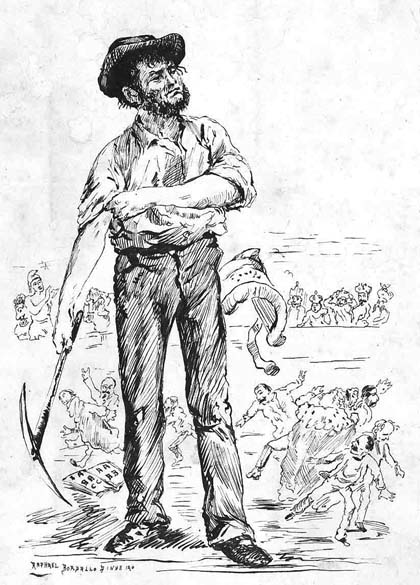
Raphael Bordallo Pinheiro (1846 1905)Ilustrador de dezenas de livros e publicações, precursor do cartaz artístico em Portugal, decorador, caricaturista político e social, jornalista, ceramista e docente. Artista da Litografia.Um nome que está intimamente ligado à caricatura portuguesa, à qual deu um grande impulso, imprimindo-lhe um estilo próprio levando a uma visibilidade nunca antes atingida. Autor da figura popular Zé Povinho que se veio a tornar num símbolo do povo português. Nasceu em 1846 em Lisboa. Cedo ganha o gosto pelas artes. Em 1860 inscreve-se no conservatório e posteriormente matricula-se sucessivamente na Academia de Belas Artes (desenho de arquitectura civil, desenho antigo e modelo vivo), no Curso Superior de Letras e na Escola de Arte Dramática, para logo de seguida desistir. Começa por tentar ganhar a vida como artista plástico com composições realistas apresentando pela primeira vez trabalhos seus em 1868 na exposição promovida pela Sociedade Promotora de Belas-Artes, onde apresenta 8 aguarelas inspiradas em costumes e tipos populares. Em 1871 recebe um prémio na Exposição Internacional de Madrid. Paralelamente vai desenvolvendo a sua faceta de ilustrador e decorador. Em 1875 cria a figura do Zé Povinho, publicada n'A Lanterna Mágica. No BrasilEm 1875 parte para o Brasil onde colabora em alguns jornais e a enviar a sua colaboração para Lisboa, voltando a Portugal em 1879 e lança O António Maria. LitografiaComo litógrafo, Bordalo Pinheiro deixou um legado notável. Compôs desenhos para almanaques, anúncios e revistas estrangeiras como El Mundo Comico (1873-74), Ilustrated London News, Ilustracion Española y Americana (1873), L'Univers Illustré e El Bazar. Fez desenhos em álbuns de senhoras, foi o autor de capas e de centenas de ilustrações em livros, e em folhas soltas deixou portraits-charge de diversas personalidades. Começou a fazer caricatura por brincadeira como aconteceu nas paredes dos claustros do edifício onde dava aulas o Professor Jaime Moniz, onde apareceram, desenhados a ponta de charuto, as caricaturas dos mestres. Mas é a partir do êxito alcançado pel'O Dente da Baronesa (1870), folha de propaganda a uma comédia em 3 actos de Teixeira de Vasconcelos, que Bordalo entra definitivamente para a cena do humorismo gráfico. Dotado de um grande sentido de humor, mas também de uma crítica social bastante apurada e sempre em cima do acontecimento, caricaturou todas as personalidades de relevo da política, da Igreja e da cultura da sociedade portuguesa. Apesar da crítica demolidora de muitos dos seus desenhos, as suas características pessoais e artísticas cedo conquistaram a admiração e o respeito público que tiveram expressão notória num grande jantar em sua homenagem realizado na sala do Teatro Nacional D. Maria II, em 6 de Junho de 1903 que, de forma inédita, congregou à mesma mesa praticamente todas as figuras que o artista tinha caricaturado. Na sua figura mais popular, o Zé Povinho, conseguiu projectar a imagem do povo português de uma forma simples mas simultaneamente fabulosa, atribuindo um rosto ao país. O Zé Povinho continua ainda hoje a ser retratado e utilizado por diversos caricaturadores para revelar de uma forma humorística os podres da sociedade. Cerâmica nas Caldas da RainhaExperimenta em 1885 trabalhar o barro e começa o fabrico da louça artística das Fábrica de Faianças das Caldas da Rainha. Após a constituição da fábrica de faiança das Caldas da Rainha, Bordalo Pinheiro dedica-se à produção de peças de cerâmica. Jarras, vasos, bilhas, jarrões, pratos e outras peças demonstram um labor criativo e decorativista. Mas Bordalo não se restringiu apenas à fabricação de loiça ornamental. Além de ter desenhado uma baixela de prata da qual se destaca um originalíssimo faqueiro que executou para o 3º visconde de S. João da Pesqueira, satisfez dezenas de pequenas e grandes encomendas para a decoração de palacetes: azulejos, painéis, frisos, placas decorativas, floreiras, fontes-lavatório, centros de mesa, bustos, molduras, caixas, e também broches, alfinetes, perfumadores, etc. No entanto, a cerâmica também não poderia excluir as figuras do seu repertório. A par das esculturas que modelou para as capelas do Buçaco representando cinquenta e duas figuras da Via Sacra, Bordalo apostou sobretudo nas que lhe eram mais gratas: O Zé Povinho (que será representado em inúmeras atitudes), a Maria Paciência, a mamuda ama das Caldas, o polícia, o padre tomando rapé e o sacristão de incensório nas mãos, a par de muitos outros. Embora financeiramente, a fábrica se ter revelado um fracasso, a genialidade deste trabalho notável teve expressão nos prémios conquistados: uma medalha de ouro na Exposição Colombiana de Madrid em 1892, em Antuérpia (1894), novamente em Madrid (1895), em Paris (1900), e nos Estados Unidos, em St. Louis (1904). O Jornalista
Rafael Bordalo Pinheiro destacou-se sobretudo como um homem de imprensa. Durante cerca de 35 anos (de 1870 a 1905) foi a alma de todos os periódicos que dirigiu quer em Portugal, quer nos três anos que trabalhou em terras brasileiras. Semanalmente, durante as décadas referidas, os seus periódicos debruçaram-se sobre a sociedade portuguesa nos mais diversos quadrantes, de uma forma sistemática e pertinente. Em 1870 lançou três publicações: O Calcanhar de Aquiles, A Berlinda e O Binóculo, este último, um semanário de caricaturas sobre espectáculos e literatura, talvez o primeiro jornal, em Portugal, a ser vendido dentro dos teatros. Seguiu-se o M J ou a História Tétrica de uma Empresa Lírica, em 1873. Todavia, foi A Lanterna Mágica, em 1875, que inaugurou a época da actividade regular deste jornalista sui generis que, com todo o desembaraço, ao longo da sua actividade, fez surgir e também desaparecer inúmeras publicações. Seduzido pelo Brasil, também aí (de 1875 a 1879) animou O Mosquito, o Psit!!! e O Besouro, tendo tido tanto impacto que, numa obra recente, intitulada Caricaturistas Brasileiros, Pedro Corrêa do Lago lhe dedica diversas páginas, enfatizando o seu papel. O António Maria, nas suas duas séries (1879-1885 e 1891-1898), abarcando quinze anos de actividade jornalística, constitui a sua publicação de referência. Ainda fruto do seu intenso labor, Pontos nos ii são editados entre 1885-1891 e A Paródia, o seu último jornal, surge em 1900. A seu lado, nos periódicos, estiveram Guilherme de Azevedo, Guerra Junqueiro, Ramalho Ortigão, João Chagas, Marcelino Mesquita e muitos outros, com contributos de acentuada qualidade literária. Daí que nestas publicações os textos e o material icónico se completem harmoniosamente. Vivendo numa época de crise económica e política, Bordalo soube manter uma independência face aos poderes instituídos, nunca calando a voz, pautando-se sempre pela isenção de pensamento e praticando o livre exercício de opinião. Esta atitude granjeou um apoio público tal que, não obstante as tentativas, a censura nunca logrou silenciá-lo. E, todas as quintas-feiras, dia habitual da saída do jornal, o leitor e observador podia contar com os piparotes costumeiros, com uma crítica a que se juntava o divertimento. Mas como era natural, essa independência e o enfrentar dos poderes instituídos originaram-lhe alguns problemas como por exemplo o retirar do financiamento d'O António Maria como represália pela crítica ao partido do seu financiador. Também no Brasil arranjou problemas, onde chegou mesmo a receber um cheque em branco para se calar com a história de um ministro conservador metido com contrabandistas. Quando percebe que a sua vida começa a correr perigo, volta a Portugal, não sem antes deixar uma mensagem: ".... não estamos filiados em nenhum partido; se o estivéssemos, não seríamos decerto conservadores nem liberais. A nossa bandeira é a VERDADE. Não recebemos inspirações de quem quer que seja e se alguém se serve do nosso nome para oferecer serviços, que só prestamos à nossa consciência e ao nosso dever, - esse alguém é um infame impostor que mente." ( O Besouro, 1878)